Die 14 aufregendsten Typografie-Trends im Grafikdesign für 2024.
Von Chunky Fonts bis hin zu Vintage Serifen - hier sind die kreativen Typografie-Trends, die das Jahr 2024 eindeutig mitbestimmen werden.
Ein typografisch spannendes Jahr liegt hinter uns, nach vielen innovativen Trends und kreativen Ideen im Umgang mit Schriften im letzten Jahr wollen wir in diesem Blog Beitrag auf die Typografie-Trends des Jahres 2024 schauen. Welche neuen Trends haben sich die letzten Monate entwickelt und welche Trends aus dem letzten Jahr sind geblieben, um auch 2024 weiter zu überzeugen.
Typografie ist ein wichtiger Bestandteil im Grafikdesign und essentiell wichtig für das Branding und die Kommunikation von Marken. Eine eindrucksvolle und ausdrucksstarke Typografie ist ein wesentliches Element für die visuelle Identität einer Marke und kann dazu beitragen, ihre Persönlichkeit, Werte und Botschaften effektiv zu vermitteln.
Darüber hinaus spielt Typografie eine entscheidende Rolle bei der Lesbarkeit und Verständlichkeit von Botschaften, sei es in Printmedien, digitalen Medien oder klassischen Werbematerialien. Eine gut durchdachte und ansprechende Typografie kann dazu beitragen, die Aufmerksamkeit der Zielgruppe zu gewinnen und die Effektivität der Kommunikation einer Marke zu steigern.
Tauchen wir also in die Zukunft der Typografie ein und entdecken wir, was der Welt des Branding im Jahr 2024 bevorsteht.
1. Chunky Fonts - ganz schön klobig
Chunky Fonts, auf Deutsch auch „ganz schön klobig“ genannt, setzen ein mutiges Zeichen in der Welt der Typografie. Diese dicken und schweren Buchstabenformen verleihen jedem Design eine starke visuelle Präsenz, erregen Aufmerksamkeit und vermitteln ein Gefühl von Kraft und Stärke.
Mit ihrem robusten und substanziellen Erscheinungsbild eignen sich klobige Schriftarten perfekt für Überschriften, Logos und Markenidentitäten, die einen bleibenden Eindruck hinterlassen möchten. Die breiten Striche und soliden Formen dieser Schriftarten vermitteln ein Gefühl von Stabilität und Selbstvertrauen, während ihre Kühnheit einen Hauch von Modernität und Eleganz verleiht.
Ob in gedruckten oder digitalen Medien – klobige Schriftarten erregen mit Sicherheit die Aufmerksamkeit des Betrachters und hinterlassen einen bleibenden Eindruck. In der sich ständig weiterentwickelnden Welt der typografischen Trends sind diese Schriftarten im Jahr 2024 definitiv etwas, das man im Auge behalten sollte.
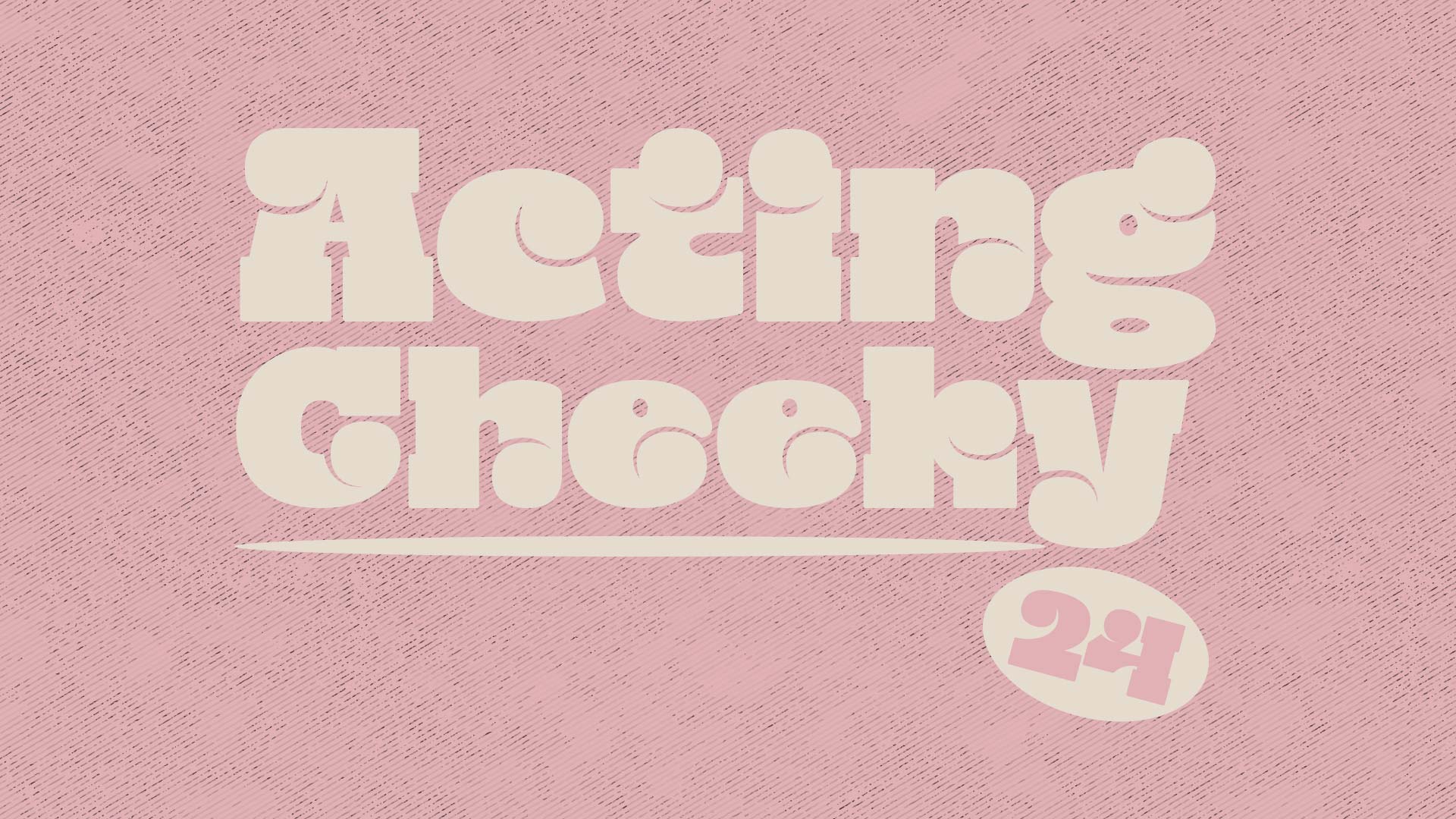
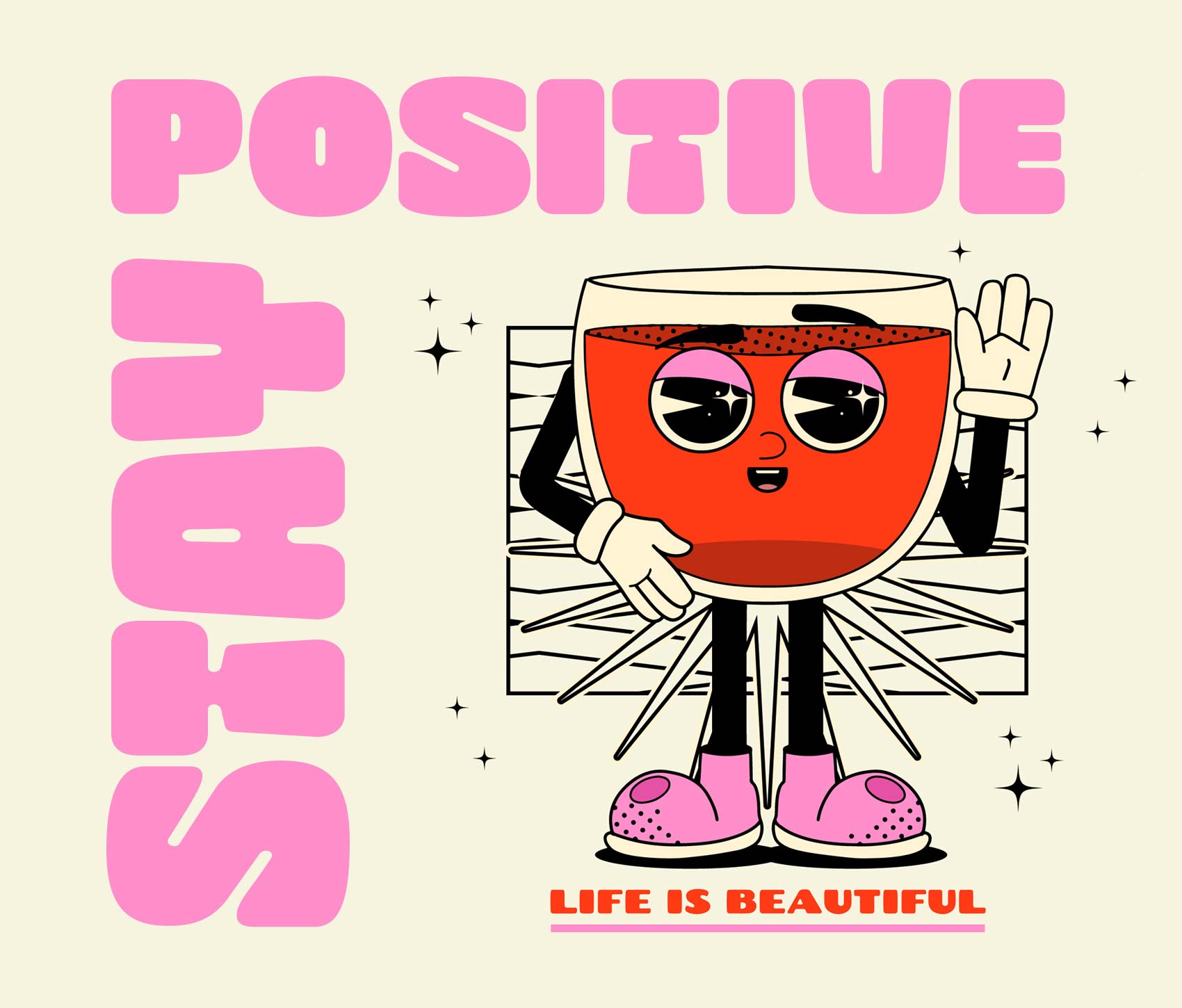
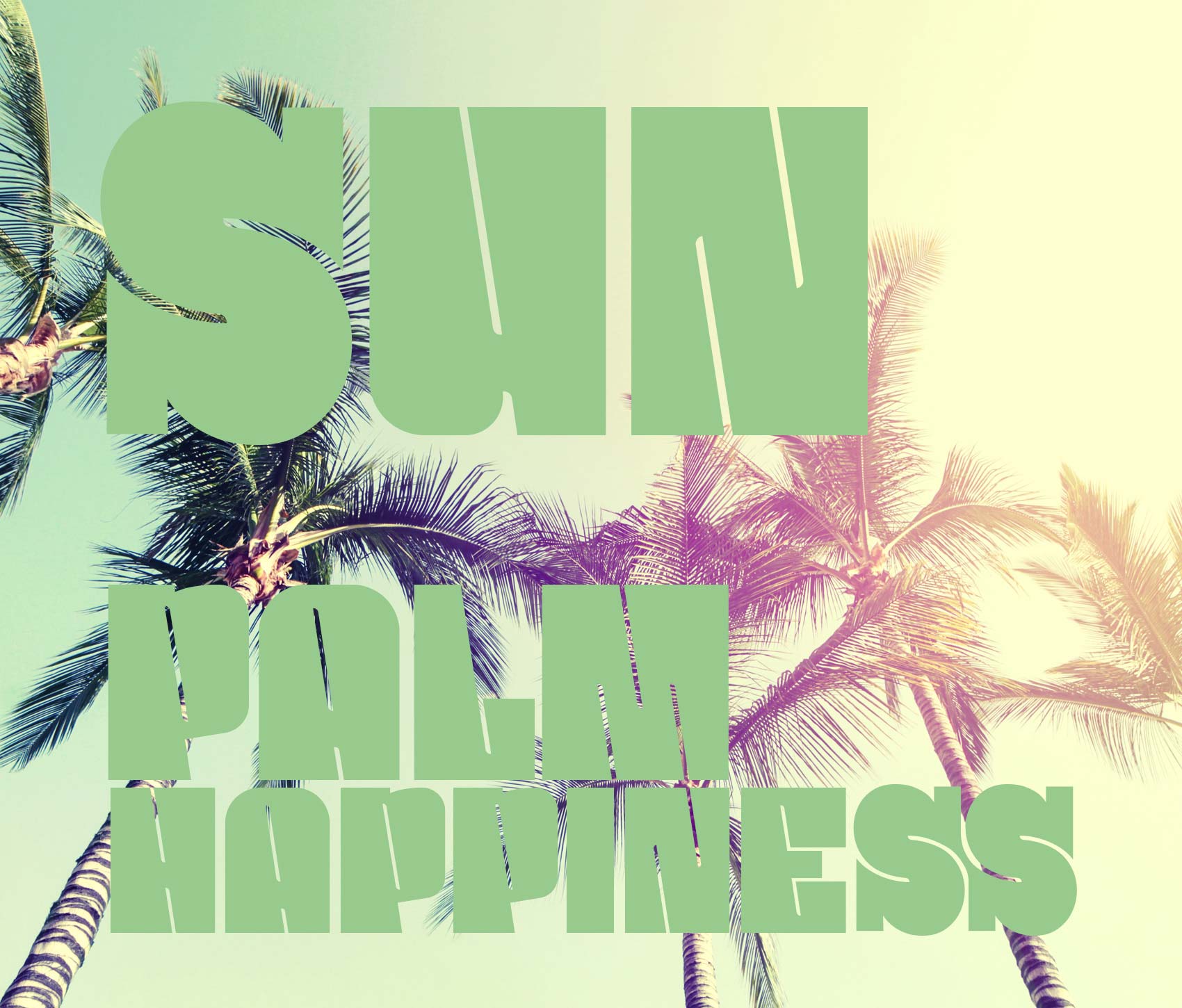
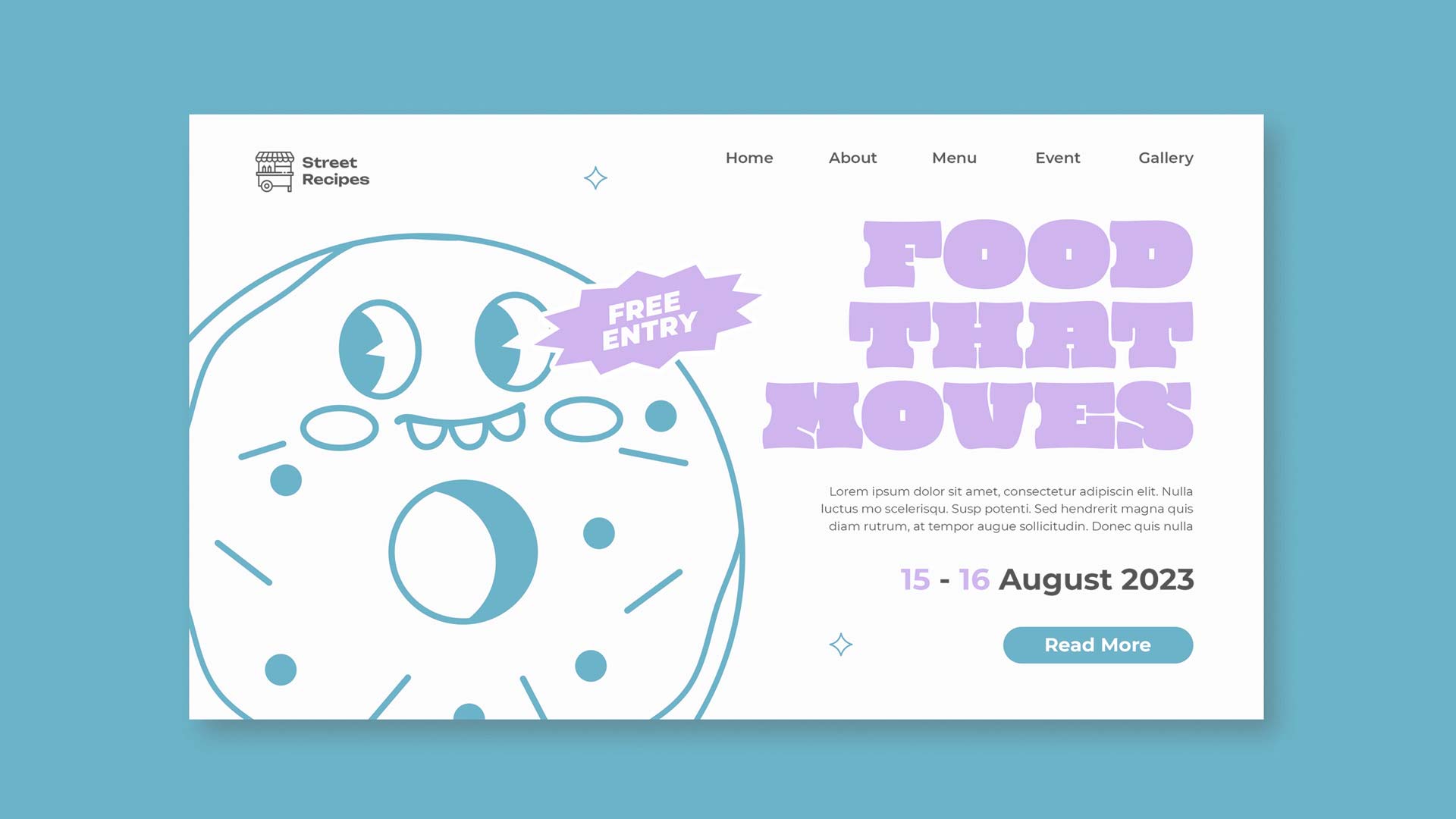
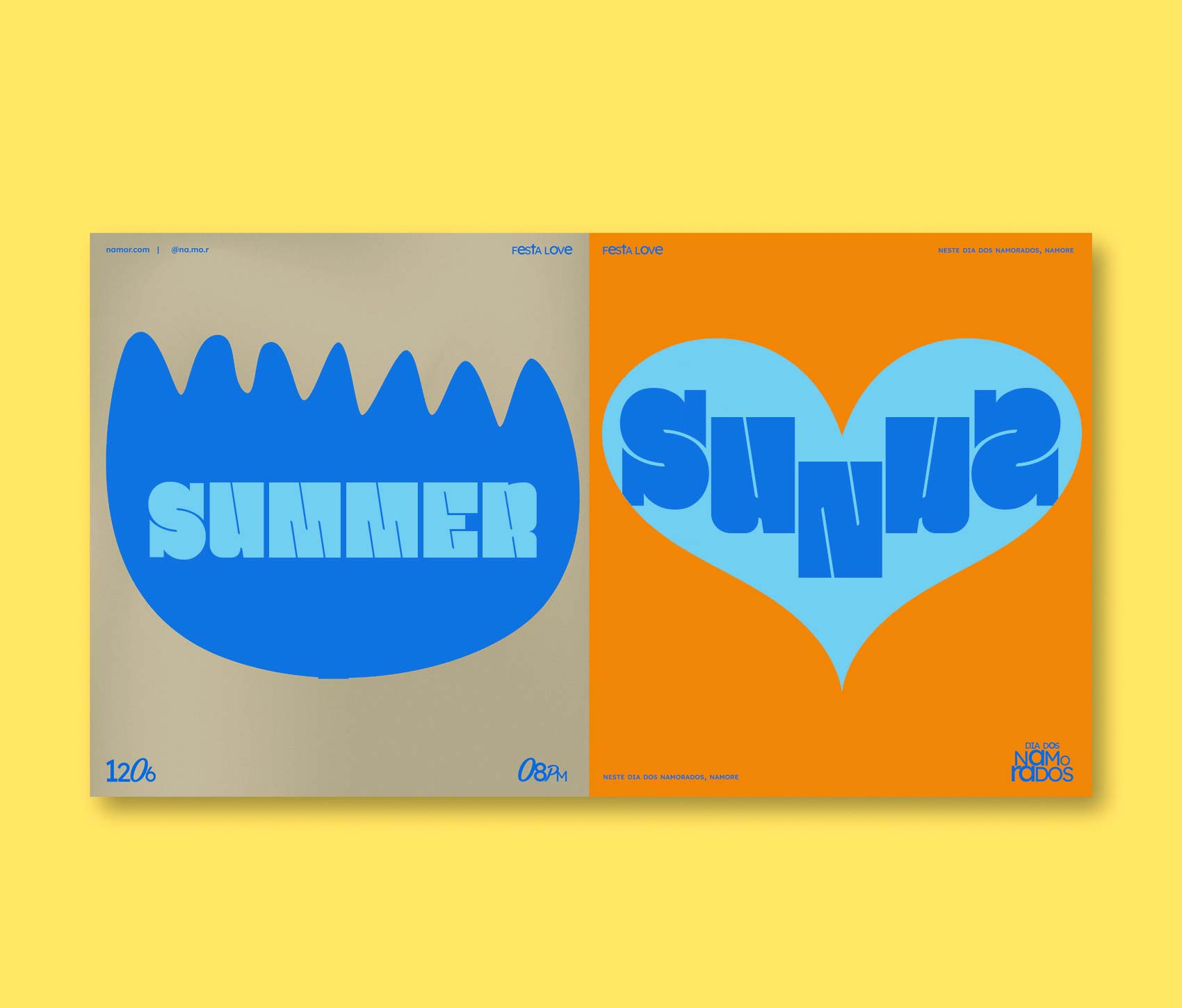
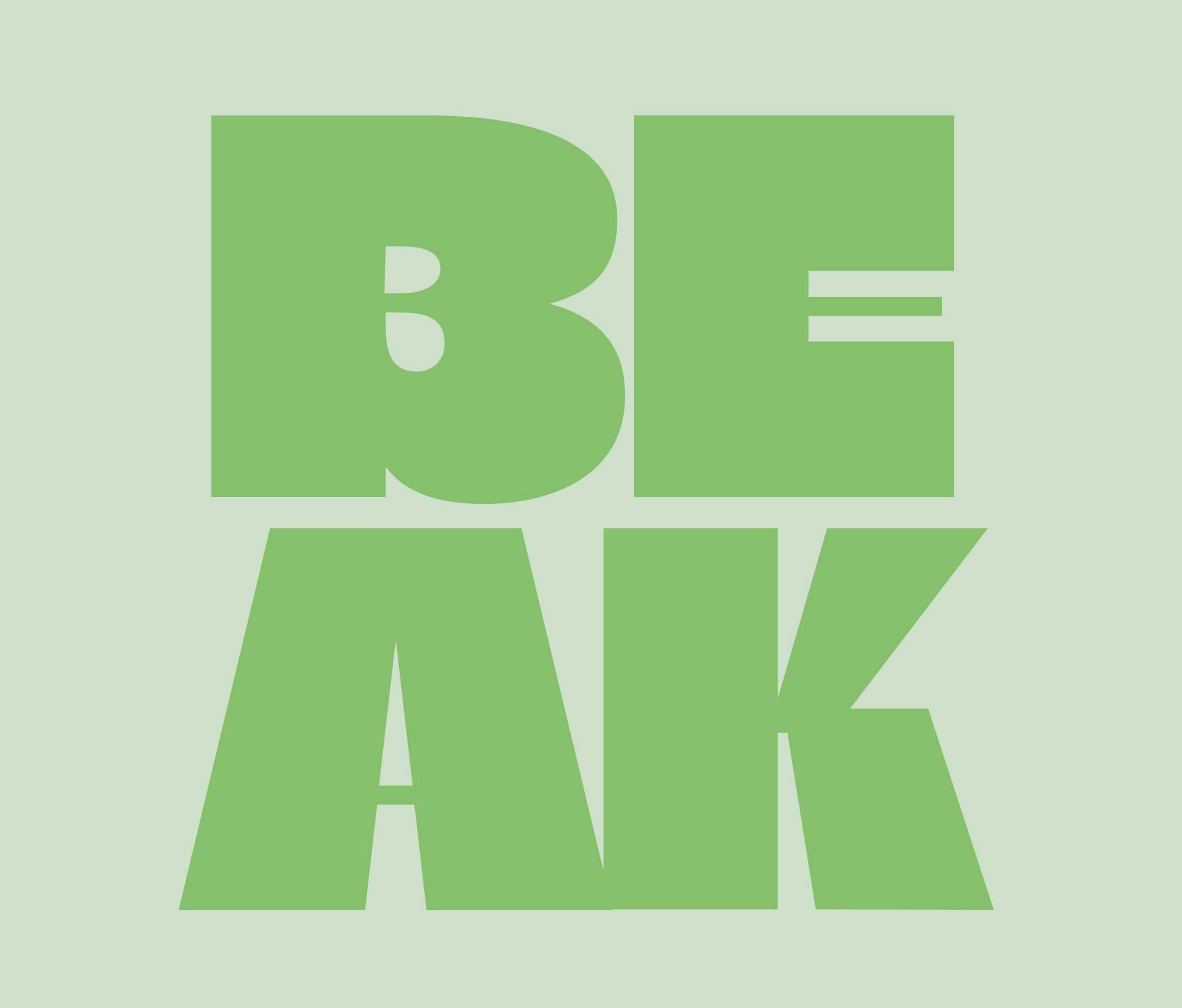
2. Curly Waves - salopp aber überzeugend
Okay, tauchen wir ein in einen der heißesten Typografie-Trends für 2024 – Curly Waves! Charakteristisch für diesen Trend sind Schriftarten mit geschwungenen Linien, lockeren Kurven und verspielten Details, die eine lebhafte und dynamische Ästhetik vermitteln. Diese Schriftarten strahlen eine gewisse Lässigkeit aus, während sie gleichzeitig eine starke visuelle Präsenz haben und eine klare Botschaft vermitteln. Der Trend Curly Waves gibt jedem Design ein Gefühl von Laune und Flair, sie verleihen Ihrem Projekt einen Hauch von Persönlichkeit und können es sofort von eintönig zu fabelhaft machen.
Die geschwungenen Linien und lockeren Kurven erzeugen eine fließende Bewegung, die das Auge des Betrachters auf sich zieht und eine dynamische visuelle Wirkung erzeugt. Sie tanzen über die Seite, fordern Aufmerksamkeit und geben ein Statement ab. Wenn Sie Ihren Designs also etwas lockeren Charme verleihen möchten, sollten Sie sich den Trend Curly Waves zu eigen machen. Vertrauen Sie Ihrer Marke, es ist ein sicherer Weg, die Aufmerksamkeit Ihres Publikums auf sich zu ziehen und einen bleibenden Eindruck zu hinterlassen.
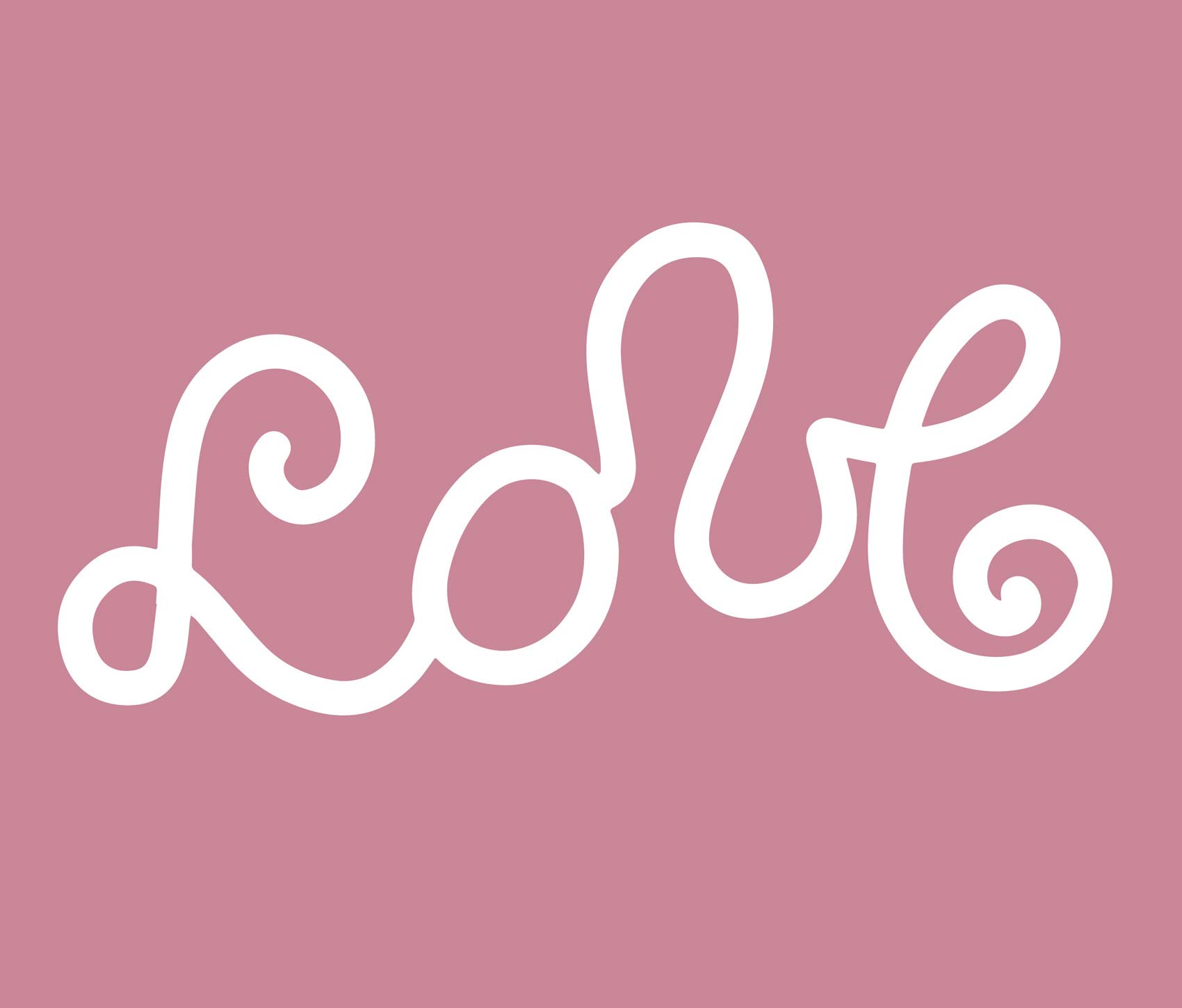
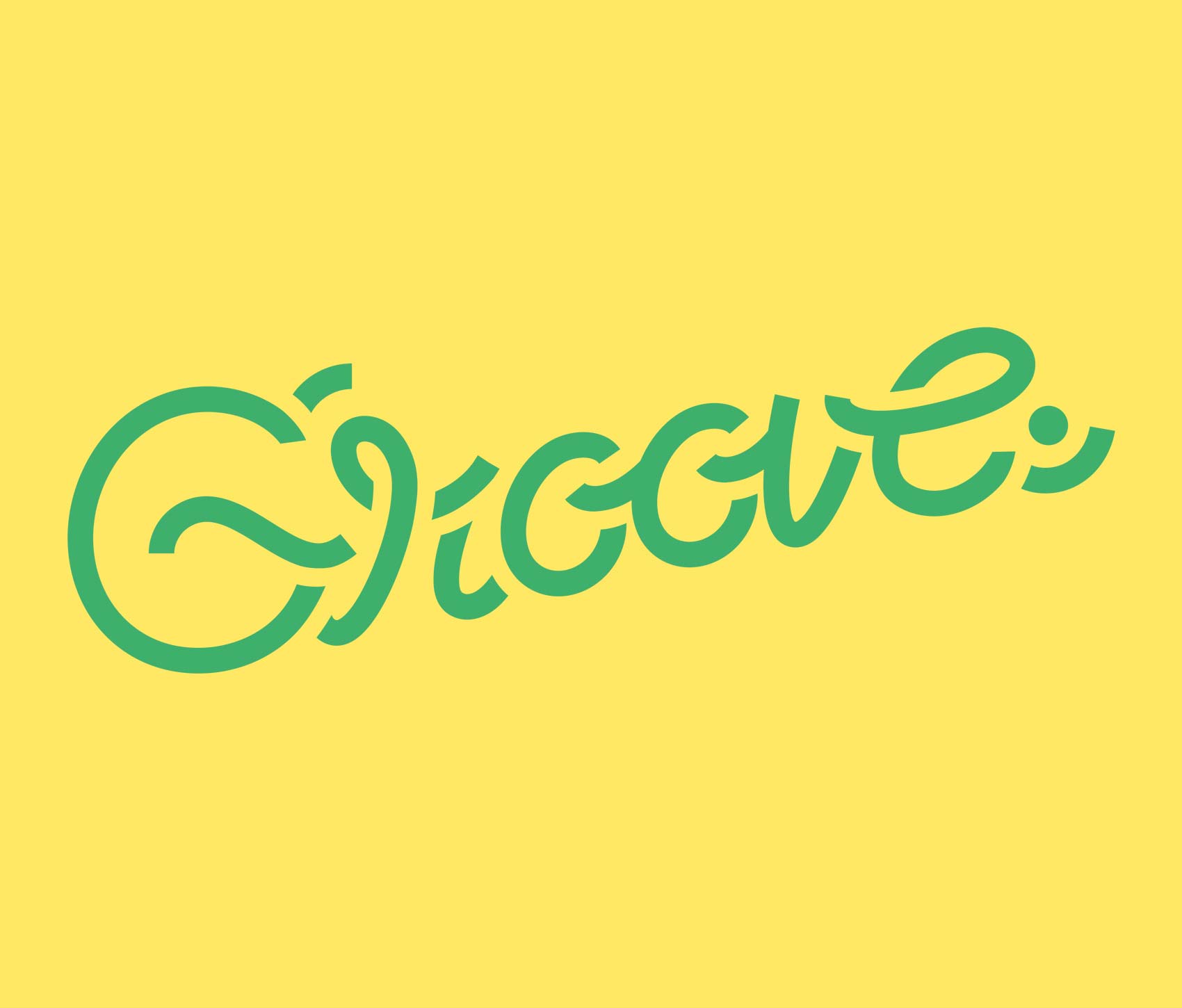
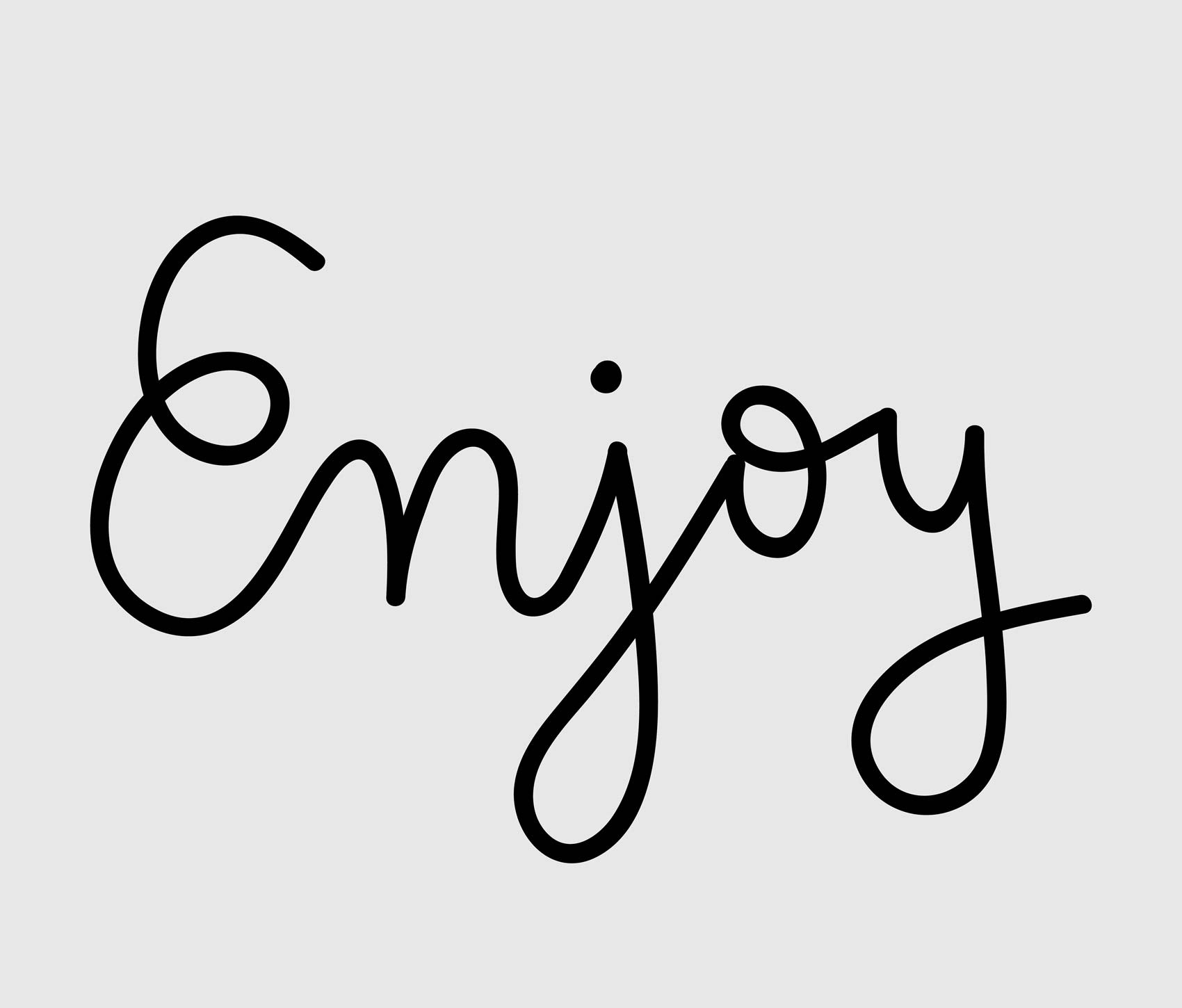
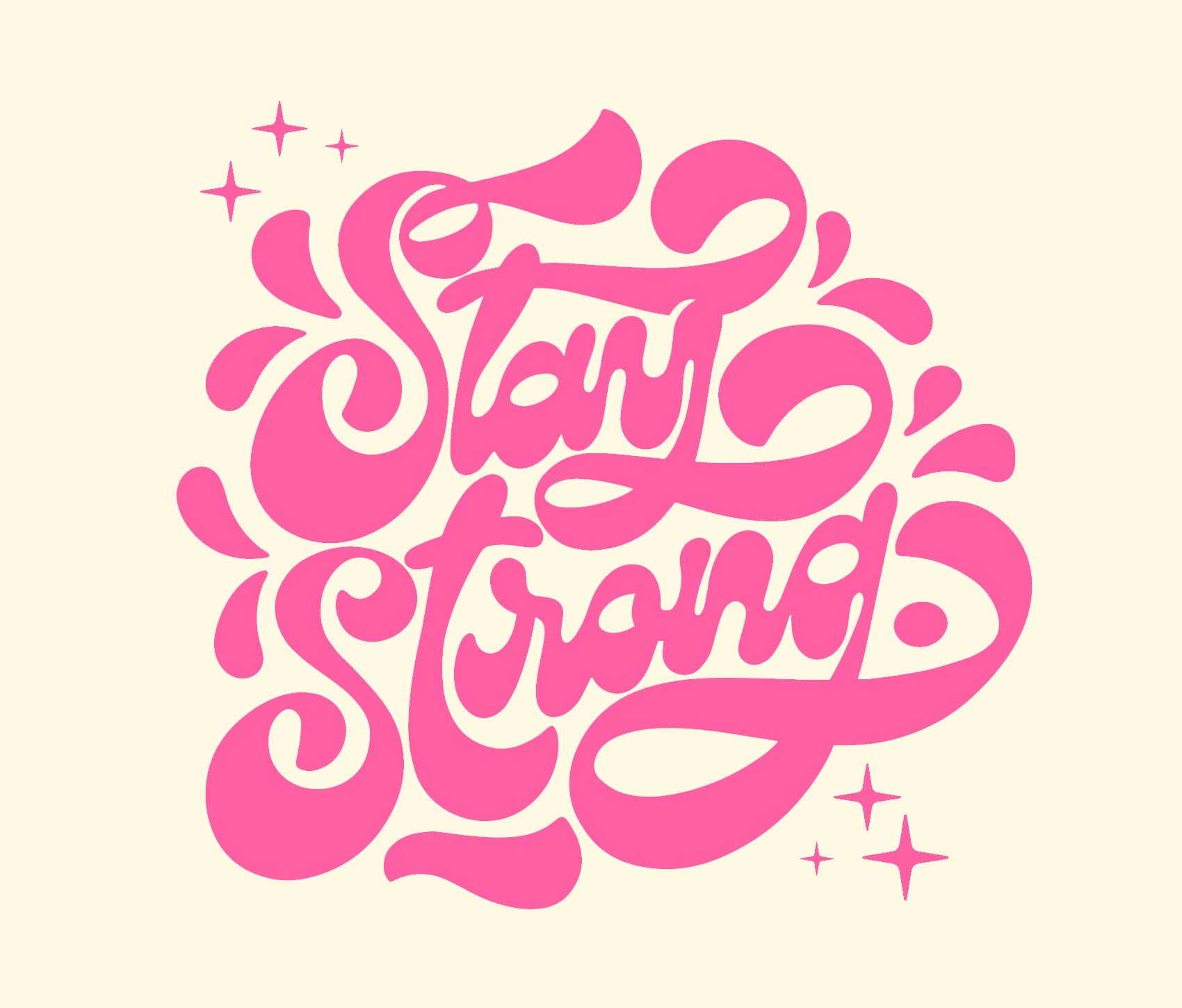
3. Mach es groß, größer, noch größer
Einer der aufregendsten typografischen Trends, auf die man im Jahr 2024 achten sollte, ist die Betonung, groß rauszukommen! Groß, größer, noch größer!
Typografie beschränkt sich nicht mehr auf kleine, subtile Textelemente. Es ist an der Zeit, mit übergroßer Schrift ein mutiges Statement zu setzen, das Aufmerksamkeit erregt und eine kühne und überwältigende Designästhetik zu schaffen, die darauf abzielt, maximalen visuellen Impact zu erzielen. Dieser Trend lädt dazu ein, Typografie in einer Größe zu präsentieren, die Grenzen überschreitet und die gesamte Bildfläche beansprucht. Dabei wird die Schrift so groß und dominant gestaltet, dass sie unausweichlich und unübersehbar wird.
Klare, fette Schriftarten mit einer starken Präsenz, die den Bildschirm dominieren, bis hin zu großformatigen Buchstaben, die ganze Layouts ausfüllen – der große Einsatz von Typografie sorgt für Dramatik und fesselt die Aufmerksamkeit des Betrachters. Zudem können Schriftarten mit markanten Serifen oder unkonventionellen Formen zusätzliche visuelle Anziehungskraft bieten. Wenn Sie also möchten, dass Ihre Designs auffallen und einen bleibenden Eindruck hinterlassen, ist es an der Zeit, den Trend zum großen Durchbruch anzunehmen!
Ganz gleich, ob es um Branding, Werbung oder Webdesign geht: Wenn Marken diesen Trend nutzen, haben sie eine aufregende Möglichkeit, die Grenzen der Typografie zu erkunden und kreative Statements zu schaffen. Durch die geschickte Nutzung von großen Schriftgrößen, kraftvollen Farben und passenden Gestaltungselementen können Marken eine beeindruckende visuelle Präsenz erzielen und ihre Botschaft mit maximaler Wirkung vermitteln.